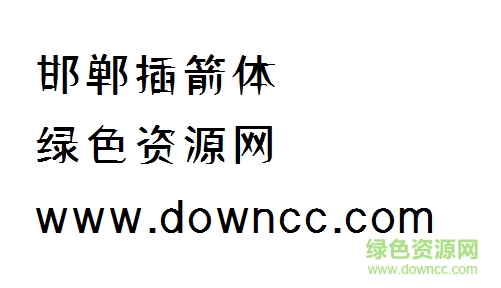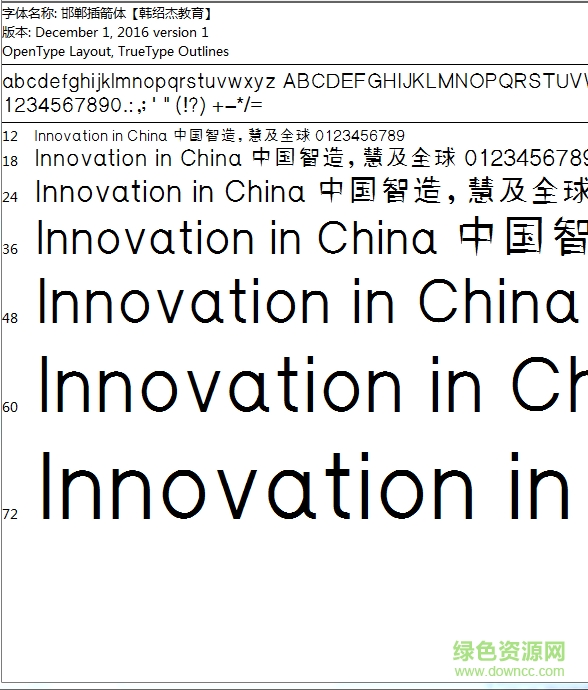
邯鄲插箭體是一款邯鄲字體軟件,插箭體字體筆畫比較有特色,首粗尾細(xì),有不錯(cuò)的筆觸情節(jié),十分有創(chuàng)意,整體效果非常好看,綠色資源網(wǎng)為您提供免費(fèi)邯鄲插箭體字體下載!
邯鄲插箭體超越了傳統(tǒng)思維模式,創(chuàng)造出新的書法藝術(shù)風(fēng)格,賦予書法特別的審美情趣,以其秀勁、爽利、古雅、飄逸之美獨(dú)領(lǐng)風(fēng)騷。袁體用筆一反秦漢以來幾千年的用筆規(guī)則,用筆直率簡(jiǎn)練,舒展挺拔,秀美爽利,與傳統(tǒng)的楷書和隸書的用筆有明顯的不同??芍^直逼秦漢另出一體,為五體之外的第六書體。
邯鄲插箭體字體盡顯插箭體的風(fēng)騷藝術(shù),非常的爽利、秀勁,闡釋了真正的插箭體魅力,喜歡的朋友歡迎到綠色資源網(wǎng)下載!